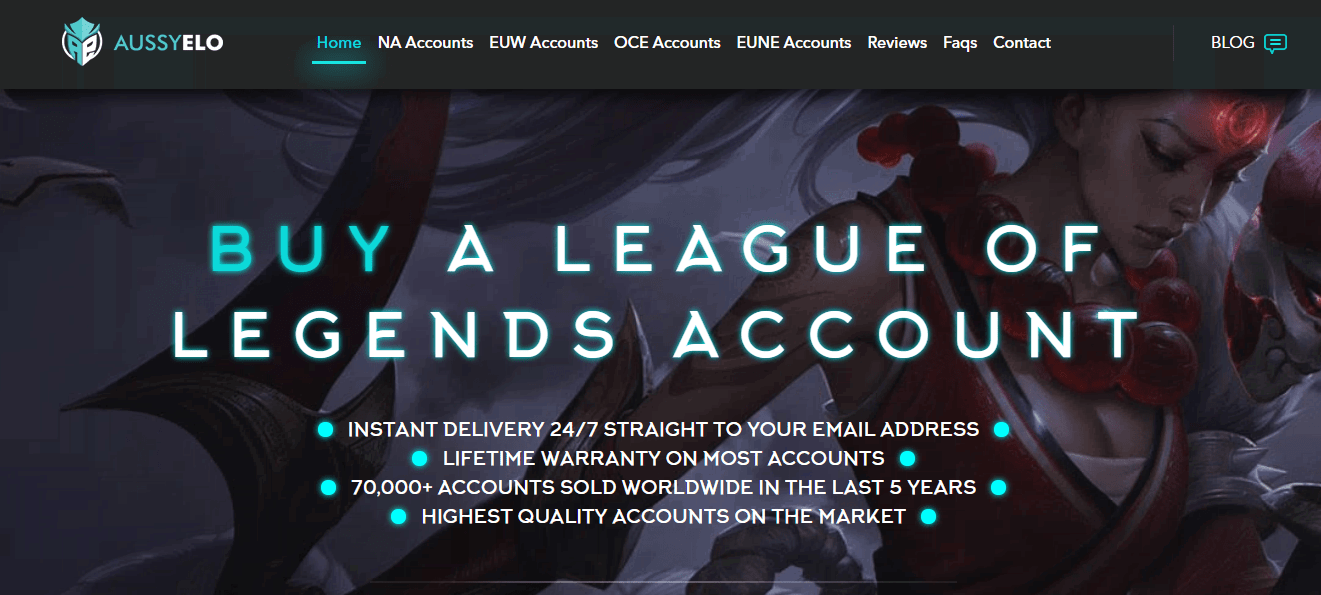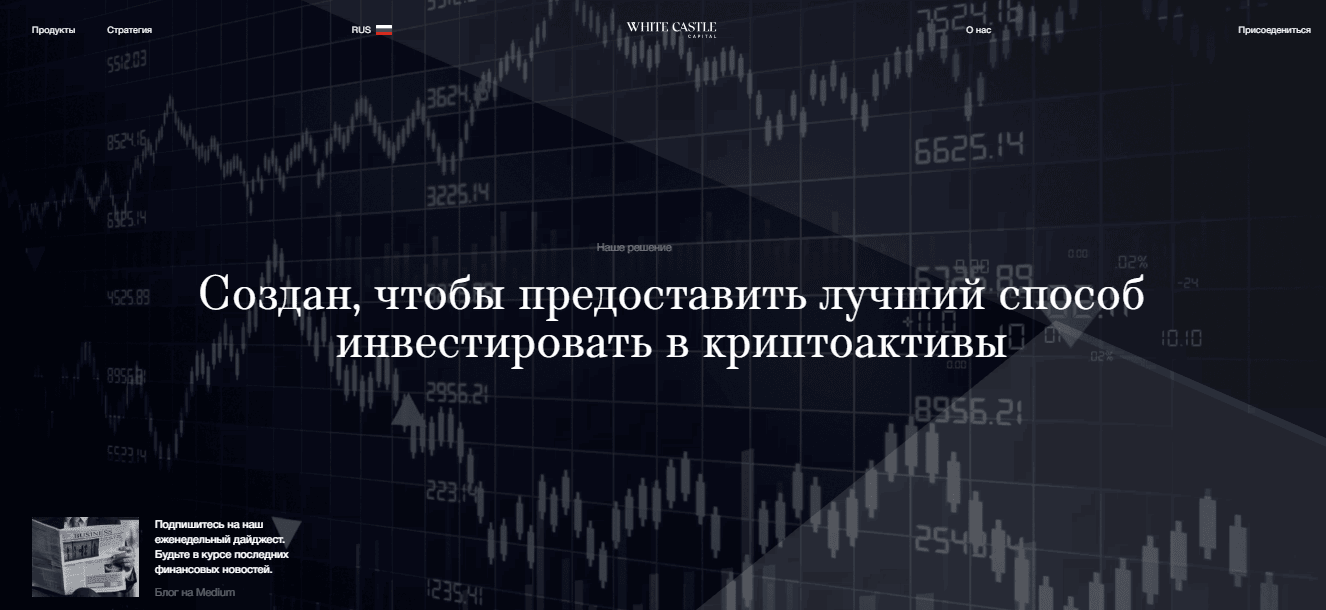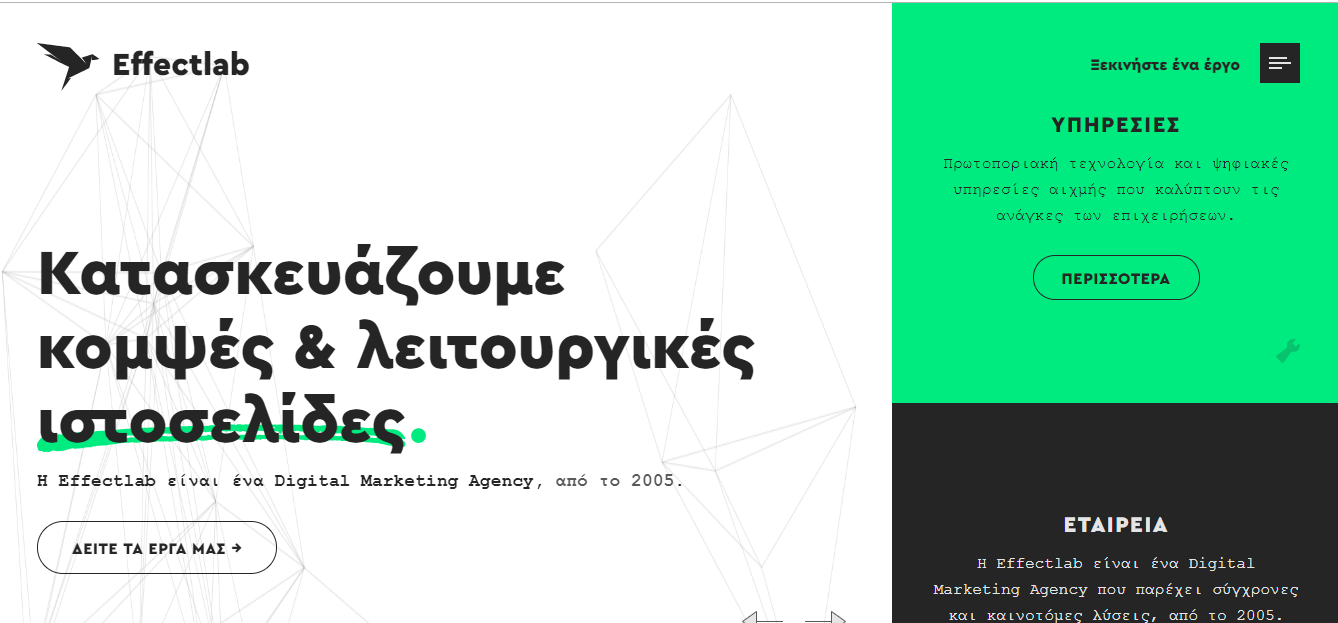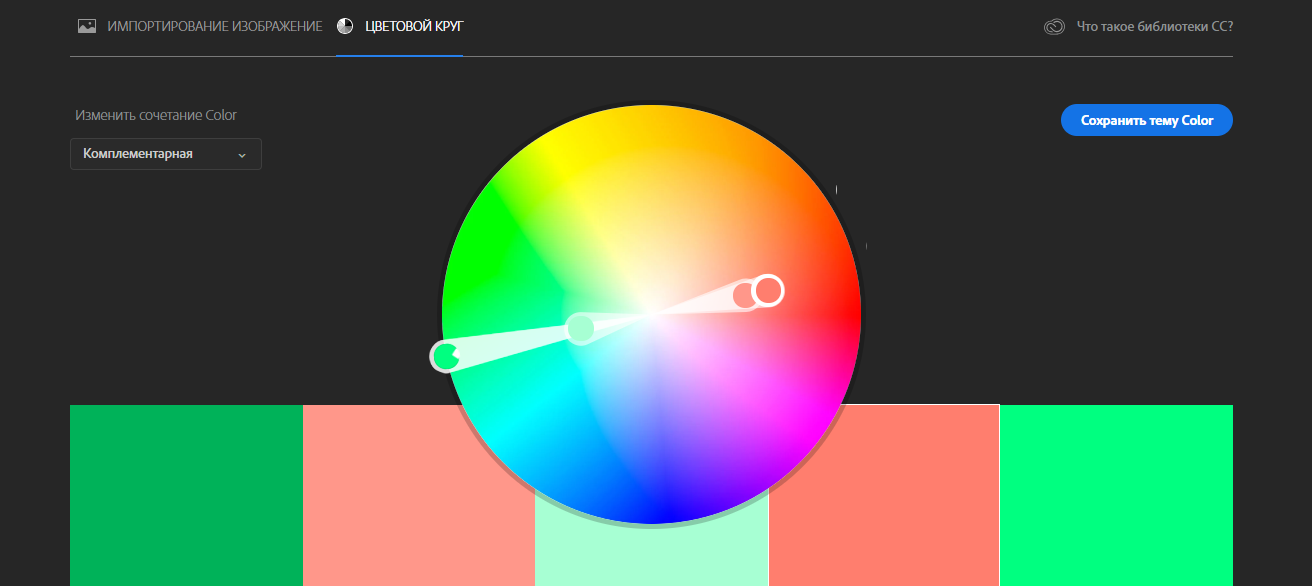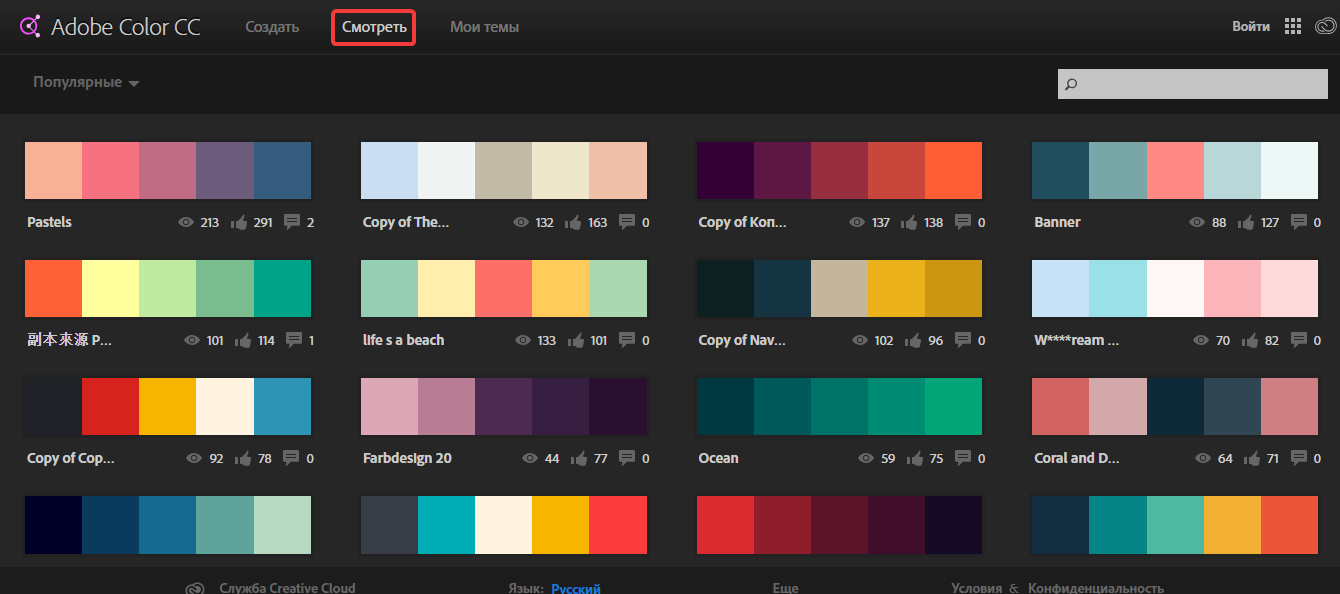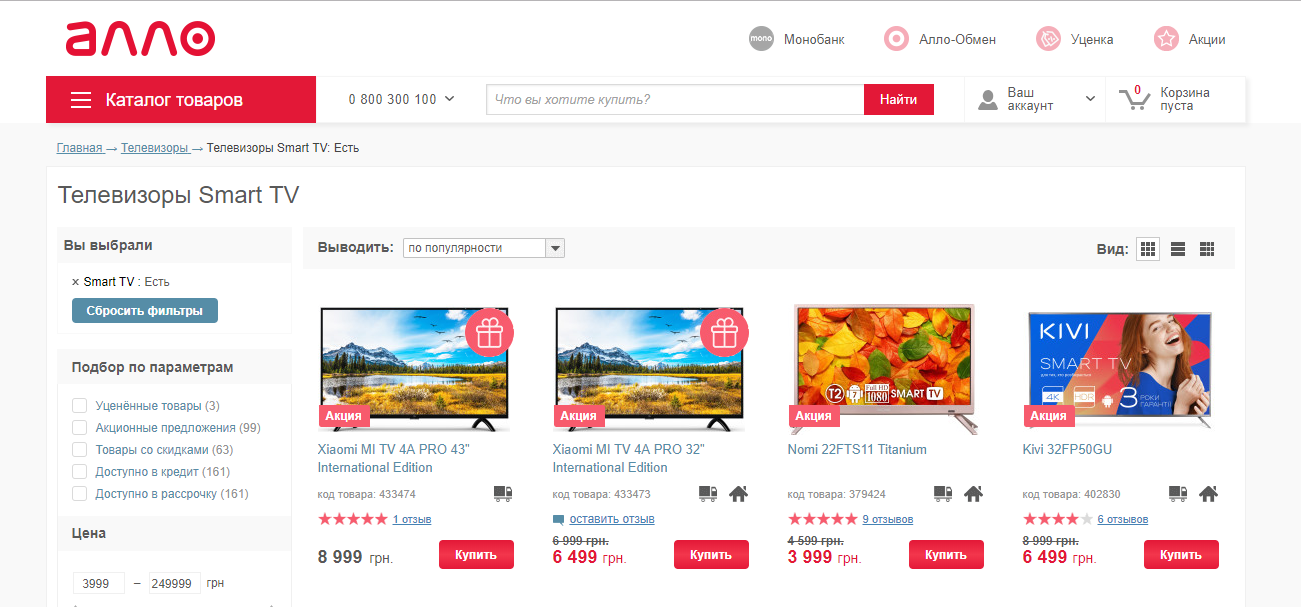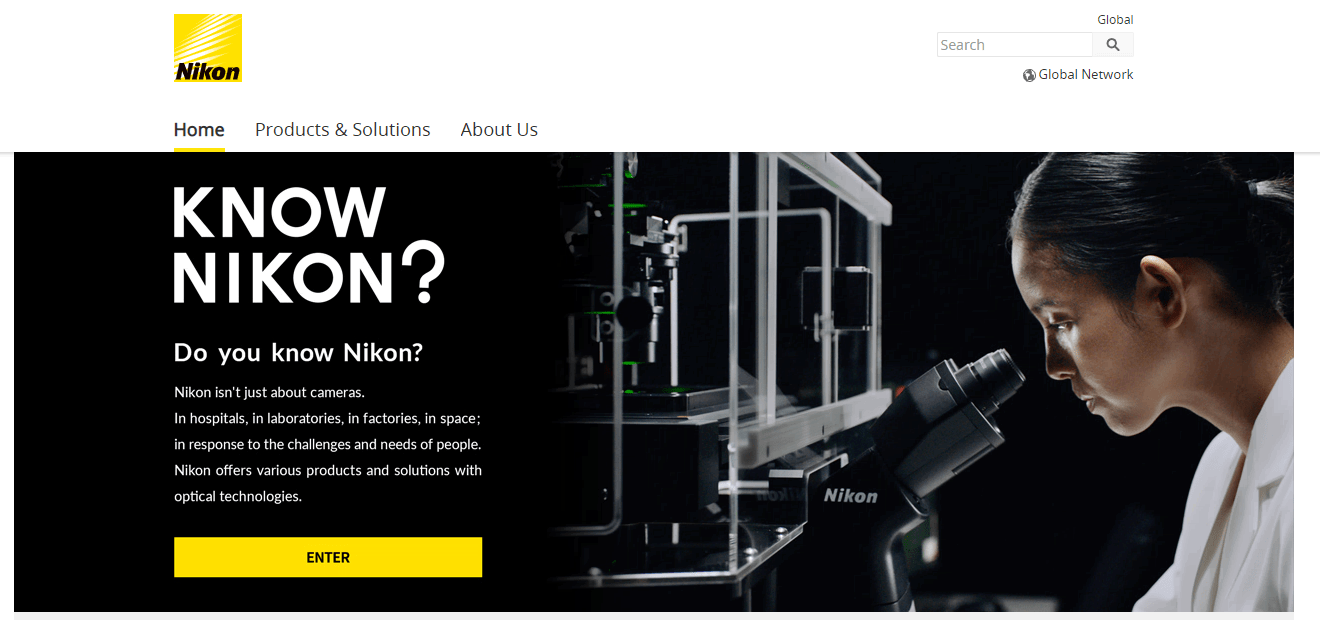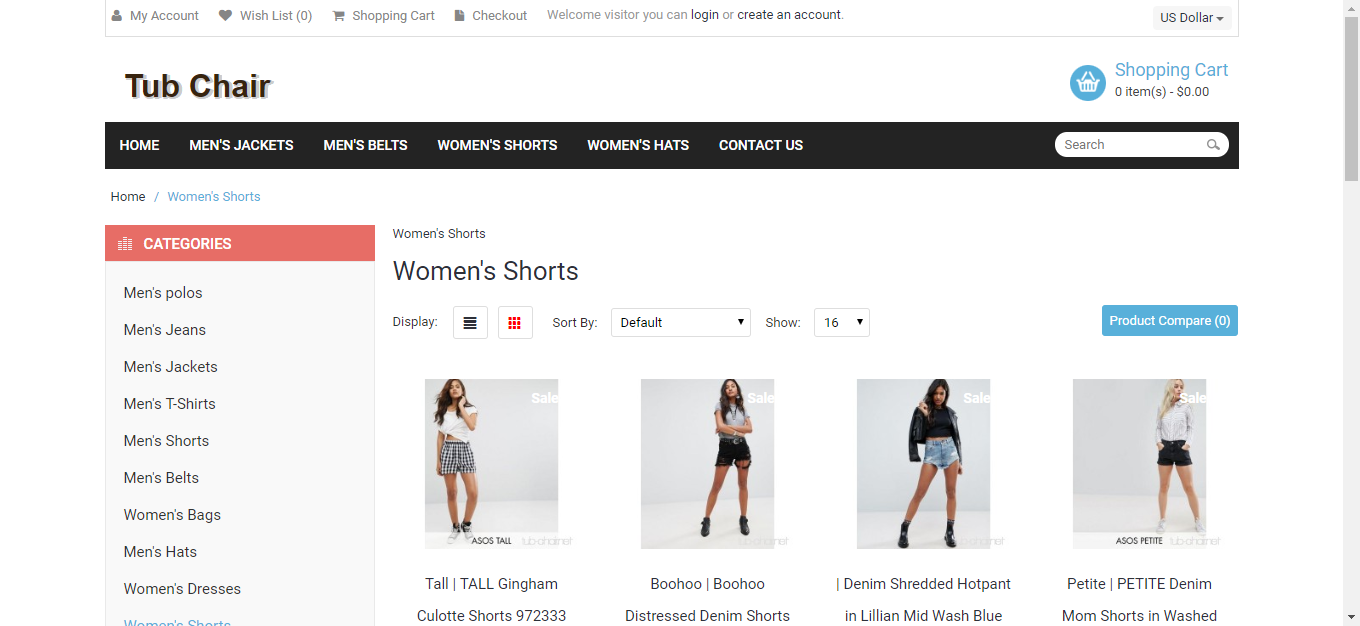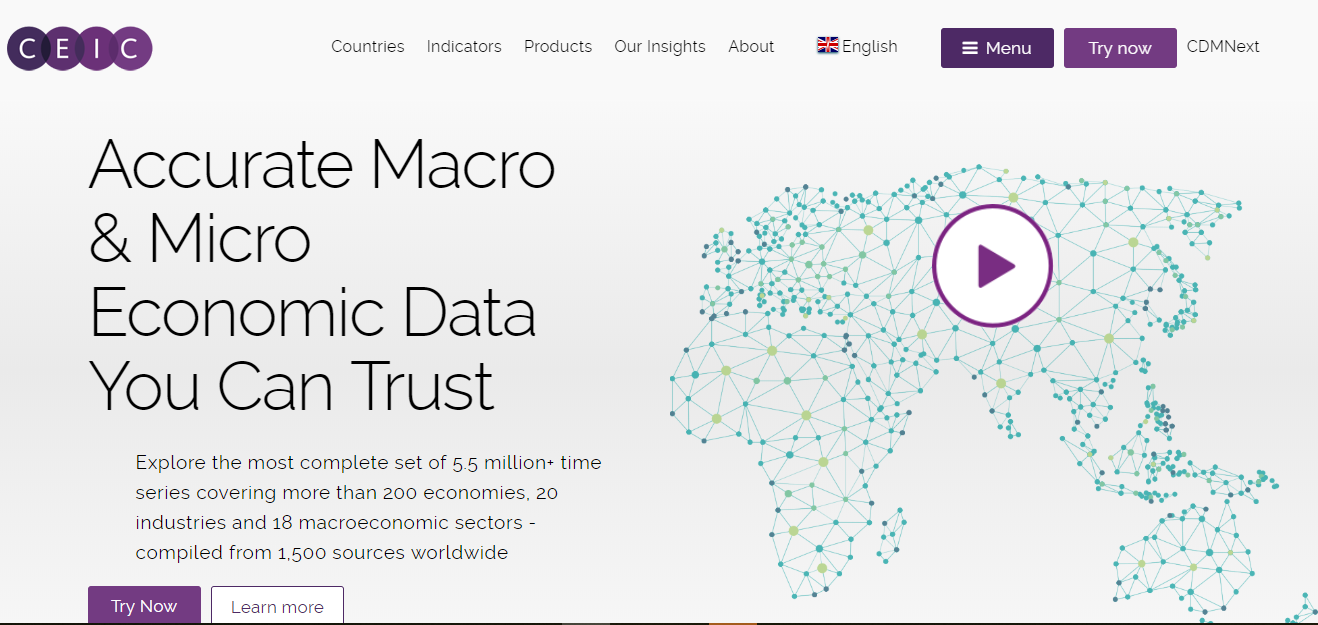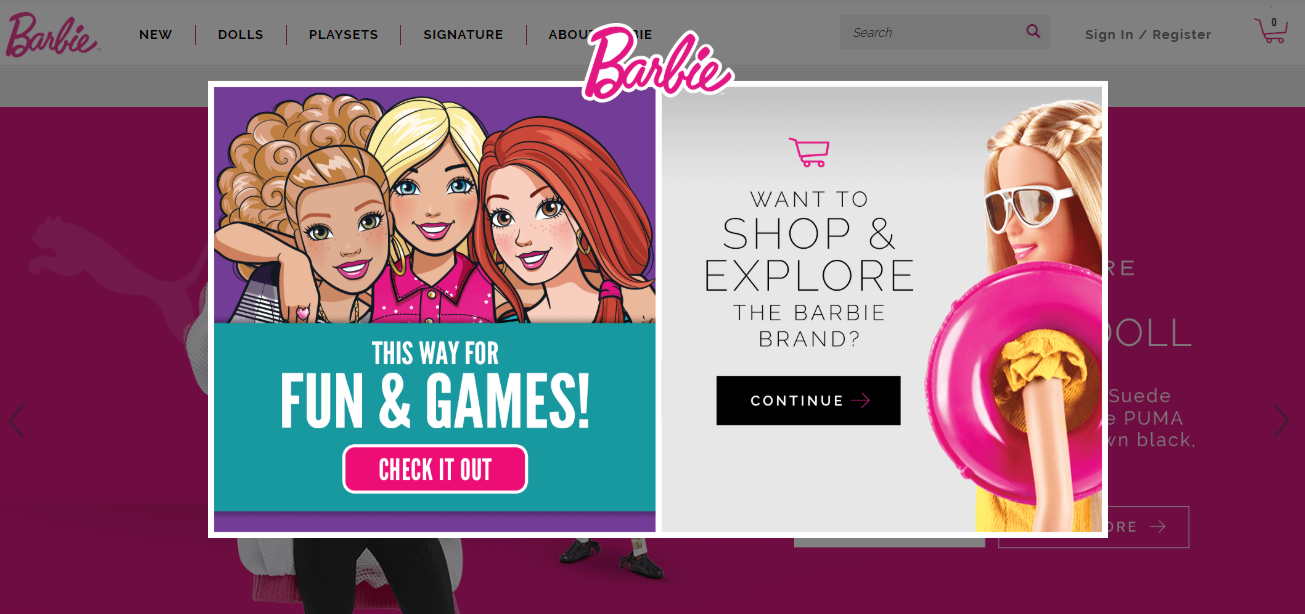
Как выбрать шрифты и цвета для сайта
Подбор цветовой гаммы и шрифтов для сайта
Для создания стильного дизайна сайта нужны базовые знания теории цвета и типографики — искусства оформления печатного текста. Подбирая цвета и шрифты, следует обращать внимание на те ассоциации, которые они традиционно вызывают у пользователей.
Как подобрать шрифты в зависимости от тематики сайта
Как доказывают научные исследования, шрифты влияют на оценку напечатанной информации. Также эксперименты подтверждают, что для разных тематик оптимальные шрифты на сайт будут отличаться, чтобы вызвать у читателей подходящие ассоциации.
Для корпоративного сайта подойдут традиционные шрифты без засечек, например, Verdana или Aria, ассоциирующиеся со строгим деловым стилем.
Для детских и развлекательных порталов стоит использовать более интересные, легкие и фантазийные шрифты, которые понравятся юной аудитории:
Шрифты для развлекательных порталов
Для научной информации более подходят шрифты с засечками — Serif. Эксперимент, проведенный в 2015 году, показал, что читатели более благоприятно воспринимают научные тексты, написанные именно такими шрифтами:
Шрифты с засечками
На восприятие читателем текста, помимо шрифта и его размера, влияют цвет, начертание, пробелы между символами и межстрочный интервал, размещение информации по колонкам. Главное, чтобы текст был разборчивым, легко читался как на компьютере, так и с портативных устройств.
Как подобрать шрифт
При выборе шрифта для сайта стоит следовать следующим рекомендациям:
• использовать не более четырех шрифтов на одной странице;
• пользоваться шрифтами без засечек (Sans-serif) для основного текста, так как на экране засечки затрудняют чтение;
• в печатной версии применять шрифты с засечками, поскольку они ассоциируются у читателей с надежностью и респектабельностью;
• для примеров программных кодов, инструкций или имитации машинописного текста использовать шрифты семейства Monospace;
• с помощью нестандартных шрифтов, например, Script и Fantasy, оформлять заголовки и делать акценты для привлечения внимания;
• использовать для заголовков и призывов к действию более крупные размеры, чем обычный текст.
Примеры шрифтов в графическом дизайне
Шрифты Craft
Шрифт на сайте — это часть вашего бренда, подумайте сначала о своем бренде выделите основные его качества и свойства.
• На примере — упаковка мороженого, где владельцы хотят подчеркнуть натуральность мороженого. Подходят отлично шрифты с имитацией тиснений букв, каллиграфия, что-то ручное, домашнее, теплое по атмосфере:
Шрифты Craft на упаковке мороженого
Шрифт Craft
Handwritten
Шрифты для бренда, имитирующие ручное написание, делают ощущения от него добрым, открытым и отзывчивым, на примере — корм для собак:
Handwritten шрифт на упаковке
Такие шрифты хороши также для детских тематик и в целом везде, где важно показать заботу и отзывчивость.
Как альтернатива такие шрифты хорошо задают неформальное настроение.
Шрифт Adlery Pro
Шрифт Amatic SC
Другие бесплатные шрифты для сайта можно изучить на специальном портале от Google или аналогах.
Serif
Шрифты с засечками отлично подойдут, если вы хотите отобразить приверженность к традициям и стабильности компании. С сочетанием яркой графики или цветов, такие шрифты здорово оживляют бренд:
Шрифты Serif
• из платных хорош Barrels:
Шрифт Barrels
Шрифт Merriweather
4
Sans Serif
Открытость, прозрачность, гибкость — все это можно отразить выразительным шрифтом без засечек. Шрифт с жирным начертанием и в сочетании с эмоциональными живыми фотографиями дает ощущение открытости бренда:
Шрифты Sans Serif
• из платных есть современный Gilroy:
Шрифт Gilroy
• из бесплатных есть Open Sans со множеством начертаний:
Шрифт Open Sans
Где лучше искать профессиональные шрифты
1
Бесплатные: fonts.google.com;
2
Платные: minttype.com.
3
На myfonts.com можно найти как платные, так и бесплатные шрифты. Стоит учесть что там могут быть бесплатными только отдельные начертания. При подборе шрифта онлайн обязательно ознакомьтесь с условиями использования и проверьте, доступны ли нужные вам элементы и языки.
Как с помощью типографики расставить акценты на важной информации
Чтобы привлечь внимание пользователя к определенному тексту, применяются различные способы:
• изменение начертания — выделение жирным либо курсивным шрифтом;
• цветовое выделение отдельных блоков информации или конверсионных элементов:
Графическое выделение конверсионных элементов страницы
• изменение цвета или размера шрифта.
Как правильно использовать пробелы в тексте
При оформлении текста нужно обращать внимание на правильное использование пробелов. Рассмотрим правила корректного оформления на примерах.